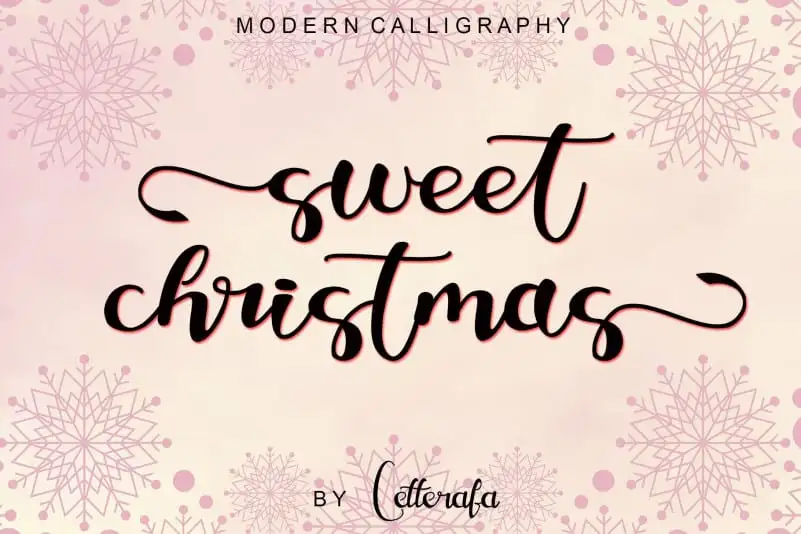
Sweet Christmas Calligraphy Font – Download Grátis
A Sweet Christmas Calligraphy Font é uma escolha perfeita para projetos design que desejam trazer um toque delicado e atraente à sua criação. Feita pelo designer Ahmad Afandi, essa fonte faz parte de uma coleção chamada Letterafa, repleta de opções únicas e bem pensadas. Sua característica mais marcante é o seu design fluido e elegante, que adquire um ar delicado e encantador a qualquer texto ou frase aplicada. Ideal para diversas tarefas gráficas, como cartões de aniversário, embalagens, identidade de marca, design manual, capa de livros, convites de casamento e embalagens, entre outros. Com uma aparência tão delicada quanto irresistível, a Sweet Christmas se torna um recurso indispensável para designers em busca de dar um toque especial à sua criação. Será que você não quer adicionar um ar mais amigável ao seu design? Então é aqui que a Sweet Christmas Calligraphy Font vem para salvar o dia!